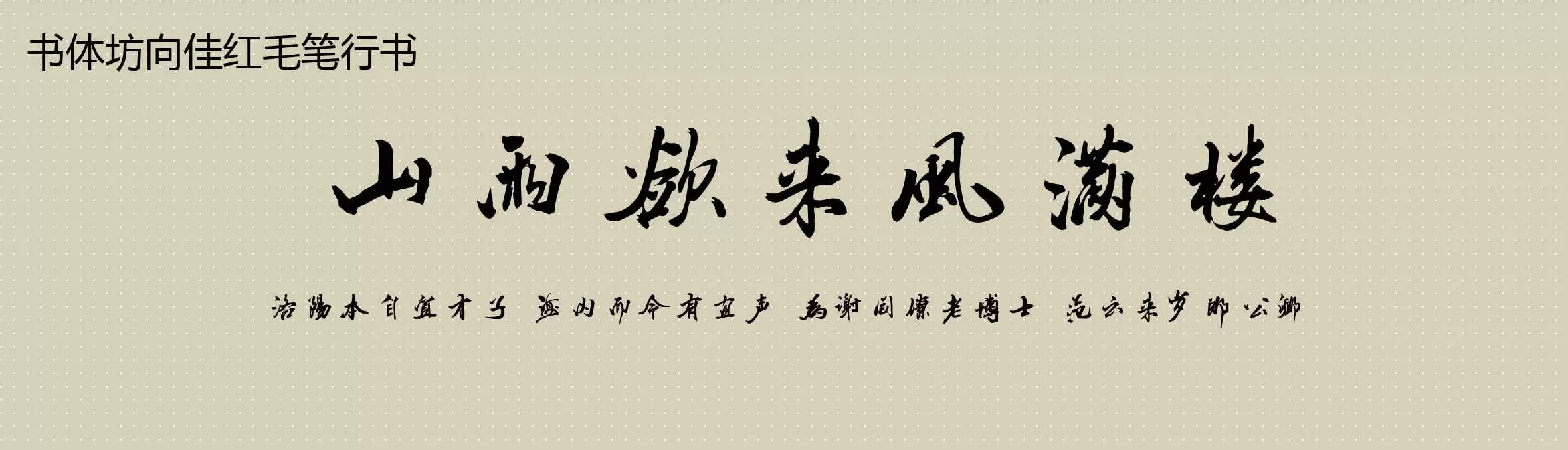
《书体坊向佳红毛笔行书》是一种优美的中文字体,以其华丽的书写风格和精致的笔画而闻名。该字体的起源可以追溯到中国古代的书法艺术,在现代时代经过不断的创新和改进而得以发展。它通常用于书写书法作品、文艺创作、广告设计等各个领域中。坊间普遍认为,《书体坊向佳红毛笔行书》是一种高雅、美观、易于识别和记忆的字体,特别适合用于书写书法题材和文艺创作。